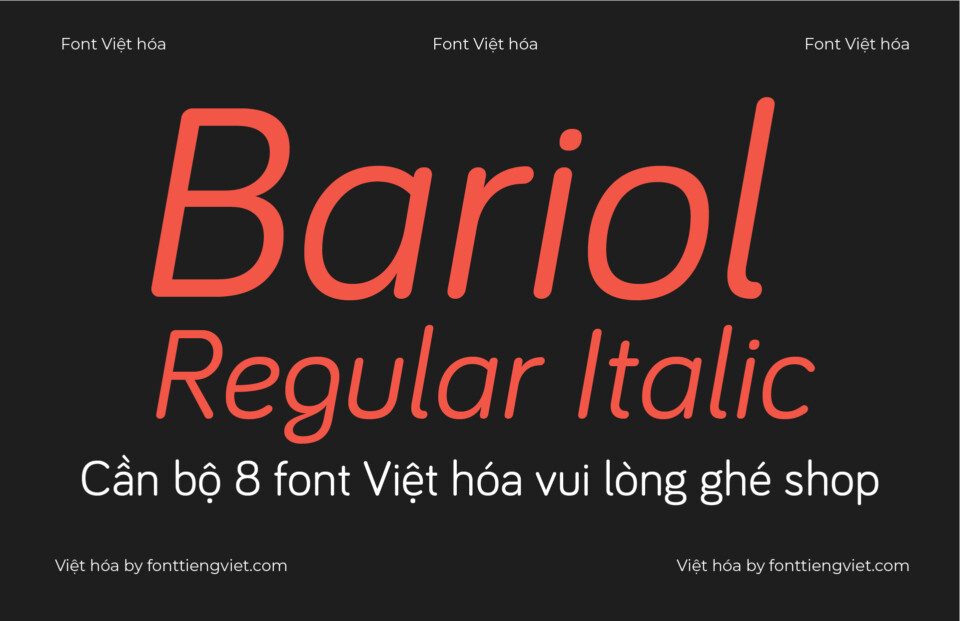
Font Việt hóa 1FTV VIP Bariol Regular Italic
Trong thế giới đồ họa hiện đại, việc lựa chọn một bộ font chữ phù hợp đóng vai trò quan trọng trong việc truyền tải thông điệp và cảm xúc của tác phẩm. Font Việt hóa 1FTV VIP Bariol Regular Italic nổi lên như một giải pháp hoàn hảo cho những ai đang tìm kiếm sự kết hợp giữa nét thanh lịch và sự trẻ trung. Đây là một phiên bản được tinh chỉnh kỹ lưỡng, giúp các nhà thiết kế tại Việt Nam dễ dàng sử dụng trong các phần mềm phổ biến mà không lo lỗi dấu. Khi nhắc đến việc tìm kiếm các bộ Font Miễn Phí chất lượng, Bariol luôn là cái tên nằm trong danh sách ưu tiên nhờ cấu trúc hình học tròn trịa và thân thiện. Với biến thể Regular Italic, bộ chữ này mang lại cảm giác chuyển động nhẹ nhàng, giúp văn bản trở nên thanh thoát và dễ tiếp cận hơn với người đọc ở mọi lứa tuổi, đặc biệt là trong môi trường giáo dục và sáng tạo nội dung số.
Đặc điểm nổi bật của Font Việt hóa 1FTV VIP Bariol Regular Italic
Lý do khiến Font Việt hóa 1FTV VIP Bariol Regular Italic trở nên phổ biến chính là nhờ thiết kế tối giản nhưng không kém phần tinh tế. Các đường cong của chữ được bo tròn mềm mại, loại bỏ đi những góc cạnh sắc nhọn thường thấy ở các phông chữ truyền thống. Điều này tạo ra một diện mạo hiện đại, sạch sẽ và cực kỳ chuyên dụng cho các giao diện ứng dụng di động hoặc trang web dành cho học sinh. Khi được Việt hóa bởi đội ngũ 1FTV, mọi ký tự đặc biệt như “ă”, “â”, “đ” hay các dấu thanh đều được căn chỉnh tỉ lệ chuẩn xác, đảm bảo tính thẩm mỹ cao nhất cho văn bản tiếng Việt.
Tính ứng dụng linh hoạt trong sáng tạo
Bộ font này không chỉ giới hạn trong các thiết kế đồ họa chuyên nghiệp mà còn cực kỳ hữu ích cho công việc hàng ngày. Font Việt hóa 1FTV VIP Bariol Regular Italic thường xuyên được sử dụng để làm tiêu đề phụ, chú thích ảnh hoặc thiết kế thiệp mời, slide bài giảng. Sự nghiêng nhẹ của phong cách Italic tạo ra điểm nhấn thị giác vừa đủ, giúp phân biệt các thành phần nội dung mà không gây rối mắt. Đối với các bạn học sinh hay thầy cô giáo, việc sử dụng phông chữ này trong các báo cáo sẽ giúp trang giấy trở nên sinh động và chuyên nghiệp hơn hẳn các kiểu chữ mặc định nhàm chán.
Cách tối ưu hóa Font Việt hóa 1FTV VIP Bariol Regular Italic cho website
Để tận dụng tối đa vẻ đẹp của Font Việt hóa 1FTV VIP Bariol Regular Italic, người dùng nên chú ý đến khoảng cách giữa các chữ cái (letter-spacing). Vì đây là kiểu chữ bo tròn, việc tăng thêm một chút khoảng cách sẽ giúp văn bản dễ đọc hơn trên màn hình độ phân giải thấp. Ngoài ra, việc kết hợp Bariol Regular Italic với các font chữ không chân (Sans-serif) khác sẽ tạo nên một hệ thống phân cấp thông tin rõ ràng. Bạn có thể dùng bản Regular cho nội dung chính và bản Italic này cho những câu trích dẫn hoặc từ khóa cần nhấn mạnh để tăng tính tương tác cho bài viết.
Kết luận về bộ font Bariol Việt hóa